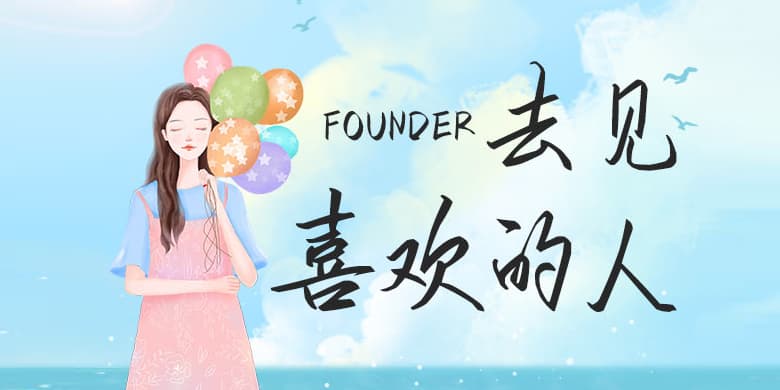
品牌:方正手迹设计师:余丹发行时间:2020字库编码:大陆简体(GB2312-80)分类:常规书写·硬笔字体属性:精品字
手写体,笔画流畅,行笔自然的连笔,较大的粗细变化,使得字体看起来有种坚韧不拔的感觉。适用于现代诗歌、短文的排版以及文化、商业类品牌的广告语设计。
品牌:方正手迹设计师:余丹发行时间:2020字库编码:大陆简体(GB2312-80)分类:常规书写·硬笔字体属性:精品字
手写体,笔画流畅,行笔自然的连笔,较大的粗细变化,使得字体看起来有种坚韧不拔的感觉。适用于现代诗歌、短文的排版以及文化、商业类品牌的广告语设计。